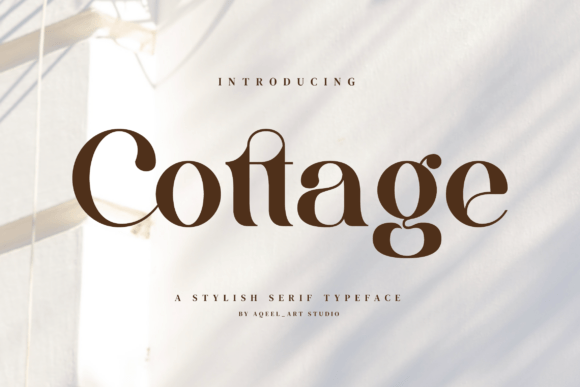
Cottage
Encontrar los elementos de diseño adecuados puede ser un desafío, pero Cottage ofrece una colección excepcional que eleva tu trabajo al instante.
Ya sea que estés creando productos POD (impresión bajo demanda), invitaciones de boda o gráficos para redes sociales, Cottage es una opción ideal.